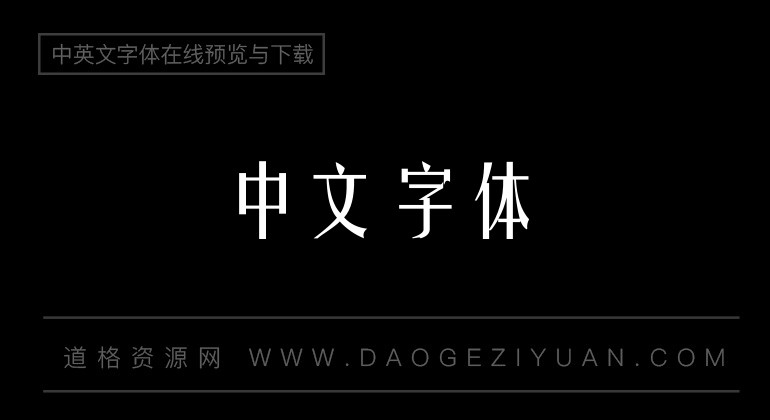
迷你简姚体
迷你简姚体是一款优雅、清新的中文字体,由著名设计师姚晨设计,由汉仪字库推出。迷你简姚体以柔和的曲线和细腻的笔画,呈现出一种简洁、大气的字体风格,是一款适用于报刊、广告等各类印刷品的非常优秀的字体。
迷你简姚体是一款非常不错的手写艺术字体,具有很好的视觉感,适合于文化类的宣传设计、商业类品牌的广告和产品包装设计以及个性化文字排版等较多场景。
迷你简姚体字符映射图